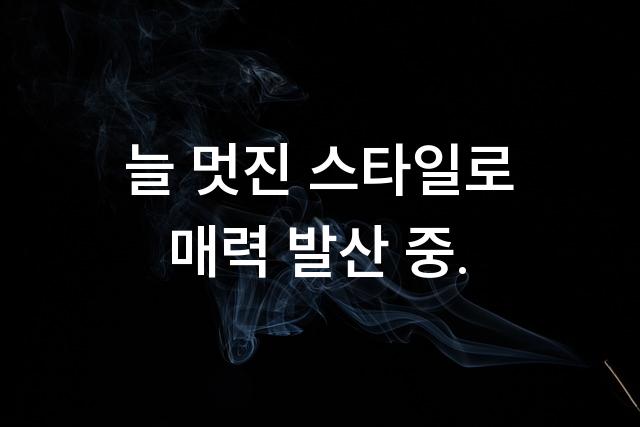
스위트는 SUNN YOUN 제작사에서 만든 기본 고딕 폰트로, 문서 작업에 최적화되어 있습니다. 세련된 디자인과 명료한 가독성으로 감성과 기능을 모두 갖추었습니다.
스위트은(는)
기본 고딕, 감성적인, 부드러움 계열의 생김새를 가지고 있으며
어린이 책, 초대장, 인사말 카드 등에서 자주 활용되며, 효과적인 메시지 전달에 적합합니다.
이 폰트는 라이프스타일, 이벤트/웨딩, 유아/가족 분야에 잘 어울리며,
따뜻한, 감성적인, 귀여운 느낌을 담고 있는 것이 특징입니다.